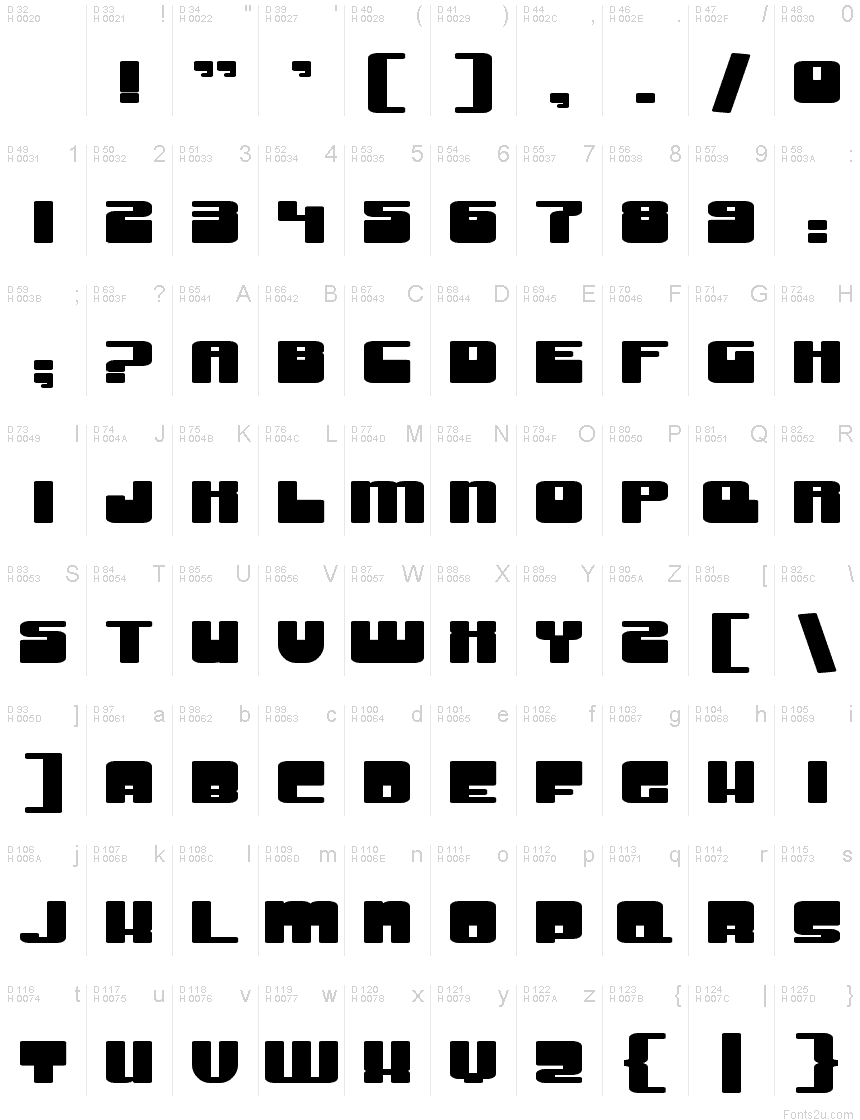
Groove Machine ExpUpright Bold
Groove Machine ExpUpright Bold od Shywedge to darmowy, groovowy krój pisma typu display. Jego masywne, blokowe litery wyglądają, jakby wycięto je z błyszczącego plastiku, a kwadratowe krzywe i ciasne światła sprawiają, że słowa zyskują solidny rytm. Futurystyczne, modularne kształty przywodzą na myśl kulturę klubową końca lat 90. i ekrany automatów do gier, nadając każdemu słowu wyrazisty, syntetyczny charakter.
Dzięki Groove Machine ExpUpright Bold Twoje nagłówki natychmiast przykują uwagę na ulotkach rave’owych, logotypach DJ-ów i producentów, tytułach gier retro, plakatach festiwalowych, okładkach na YouTube czy grafikach na gadżetach. Ten darmowy font najlepiej sprawdza się w dużych rozmiarach, gdzie jego grube formy i kanciaste światła wewnętrzne robią prawdziwe wrażenie. Zestaw go z prostym, lekkim bezszeryfowym krojem w tekstach uzupełniających, aby zachować klimat groove’u i czytelność przekazu.